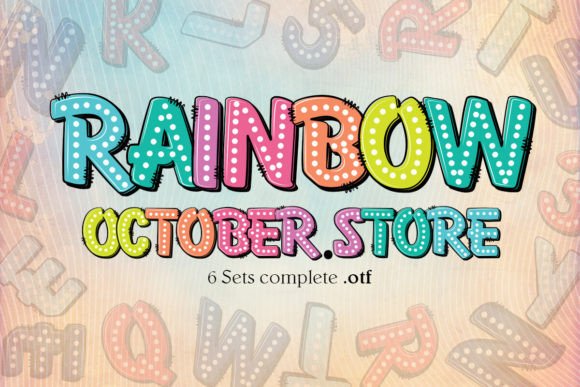
Rainbow Font
Rainbow Font – أضف لمسة إبداعية وملونة لتصاميمك!
اكتشف Rainbow Font، الخط المثالي للمبدعين الذين يبحثون عن لمسة من الحيوية والألوان في تصاميمهم. يتميز هذا الخط بألوان متدرجة تنبض بالحياة، مما يجعله الخيار المثالي للمشاريع الإبداعية مثل:
✅ الشعارات والعلامات التجارية
✅ التصاميم الرقمية والمطبوعات
✅ وسائل التواصل الاجتماعي والبطاقات الدعائية
✅ المشاريع التعليمية والمحتوى التفاعلي
لماذا تختار Rainbow Font؟
???? ألوان زاهية ومتناسقة تضيف جاذبية بصرية
أضف لمسة إبداعية وفريدة إلى أعمالك مع Rainbow Font، واجعل تصاميمك أكثر تألقًا وجاذبية! ????✨